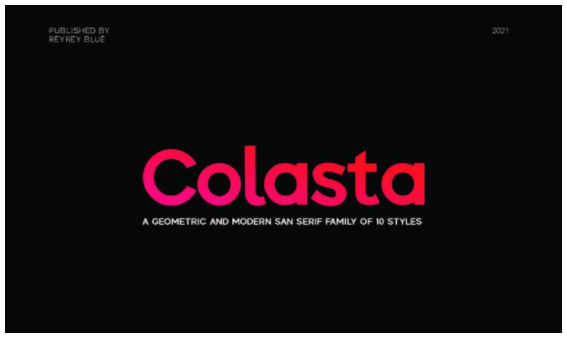
Название: Colasta Font (2021)
Colata - это новое семейство геометрических шрифтов sans-serif, которые привносят свежий, современный вид в любой дизайн. Colata представлена в 10 стилях, каждый из которых содержит малые прописные буквы и глифы для нескольких языков. Этот шрифт очень подходит в качестве текста с отображениями для различных видов брендинга, рекламы, плакатов, баннеров, упаковки, заголовков новостей, журналов, веб-сайтов, дизайна логотипов, баннеров, дизайна социальных сетей и, конечно, вы можете использовать многое другое.